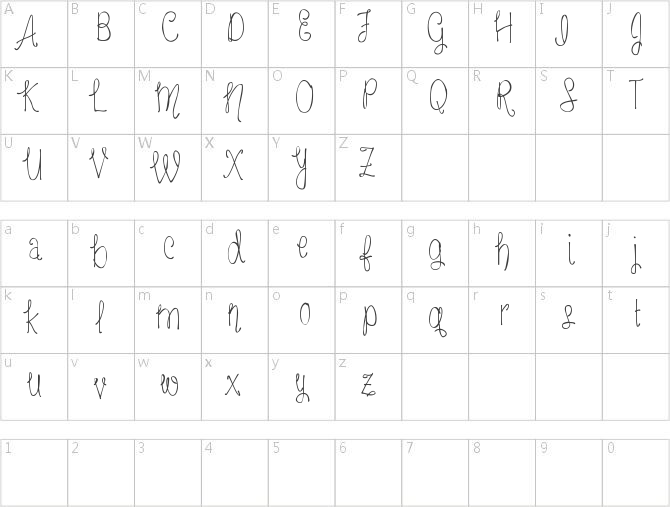
MRF FreckledLemonade Demo
MRF FreckledLemonade Demo介紹
MRF FreckledLemonade Demo字體字庫是一款讓人賞心悅目、百看不厭的英文字體,適合各類廣告和產品包裝設計應用,字體大小0.03MB,格式為ttf字體,上傳用戶是welking,作者/版權方為未知